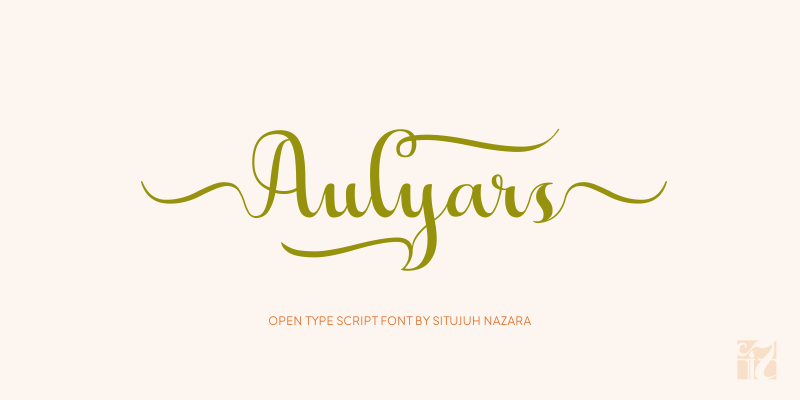
A Aulyars Script Font é uma escolha ideal para aqueles que buscam uma fonte elegante e criativa para trabalhos pessoais ou comerciais. Desenvolvida pelo designer Situjuh Nazara, ela oferece um estilo suave e fluido, perfeito para qualquer aplicação onde você deseja transmitir personalidade e sofisticação. Com uso exclusivo gratuito para clientes de personal use, essa fonte permite uma expressão artística sem limite. No entanto, para quem busca usar a Aulyars Script Font em um contexto comercial, a opção de contribuição pode ser feita através da plataforma PayPal do próprio designer, Situjuh , ou pelo site da Creative Fabrica, onde também está disponível o licenciamento de fontes comerciais. Para qualquer dúvida ou sugestão, não hesite em entrar em contato diretamente com o criador por meio de e-mail ou comentando em seu site. Com a Aulyars Script Font, você pode transformar seus projetos digitais em verdadeiros cartões postais do design moderno e sofisticado. Independentemente da categoria específica dos seus trabalhos, essa fonte é uma ótima escolha para qualquer aplicação onde o estilo contínuo de um título ou a expressão detalhada de um texto serão importantes.